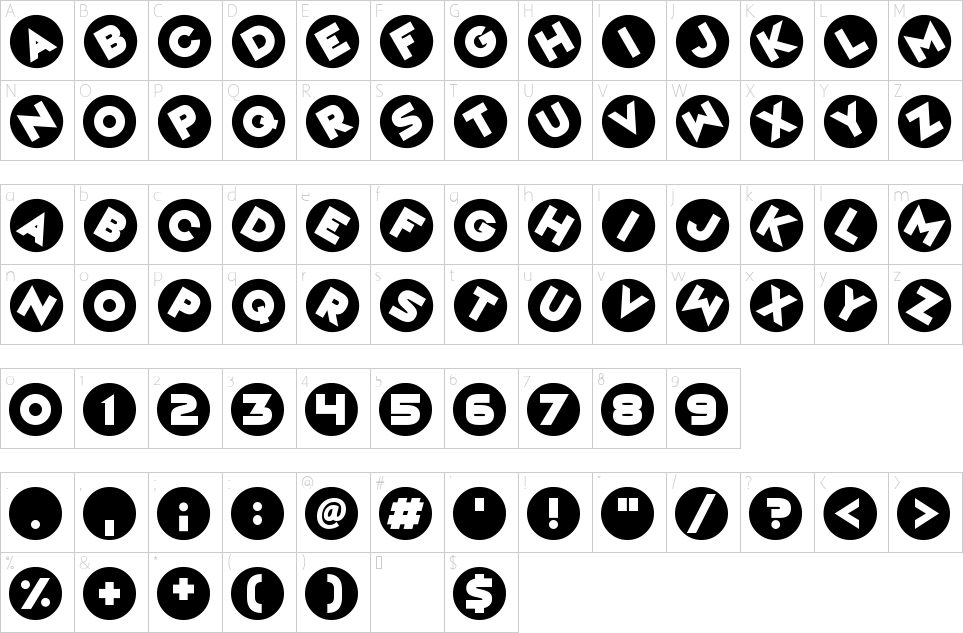
Descubra Magic Marbles, uma fonte única e elegante que combina a beleza simples das bolinhas mágicas com um toque de modernidade. Esta fonte foi criada por Darrell Flood e é uma escolha ideal para quem busca uma fonte diferente e divertida para projetos diversos. Com sua simplicidade e beleza, Magic Marbles é perfeita para criar designs criativos e divertidos, seja para o blog, a página de redes sociais, ou até mesmo para o projeto de sua decoração. Para quem busca uma fonte única e com uma qualidade de trabalho impecável, Magic Marbles é uma excelente escolha. Com uma baixa estatística de downloads, você pode garantir a exclusividade e a personalização de sua marca. Que tal adicionar Magic Marbles à sua lista de fontes favoritas?